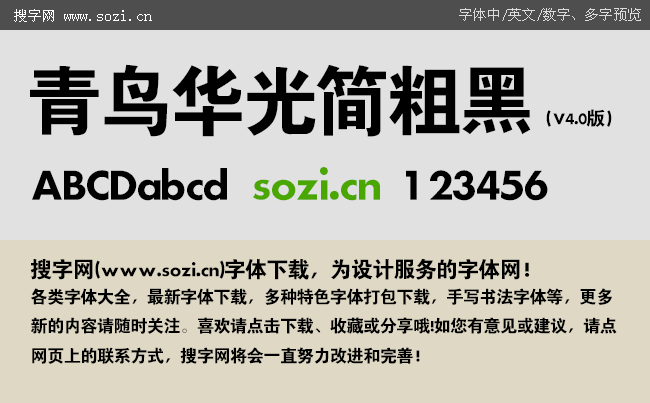
青鳥(niǎo)華光簡(jiǎn)粗黑
搜字網(wǎng)提供一款青鳥(niǎo)華光簡(jiǎn)粗黑字體下載,該字體筆劃整齊劃一,字形端正,美觀簡(jiǎn)潔,粗壯醒目,易于閱讀,適用于樣本畫(huà)冊(cè),報(bào)紙排版,網(wǎng)頁(yè)標(biāo)題等廣告設(shè)計(jì)應(yīng)用。